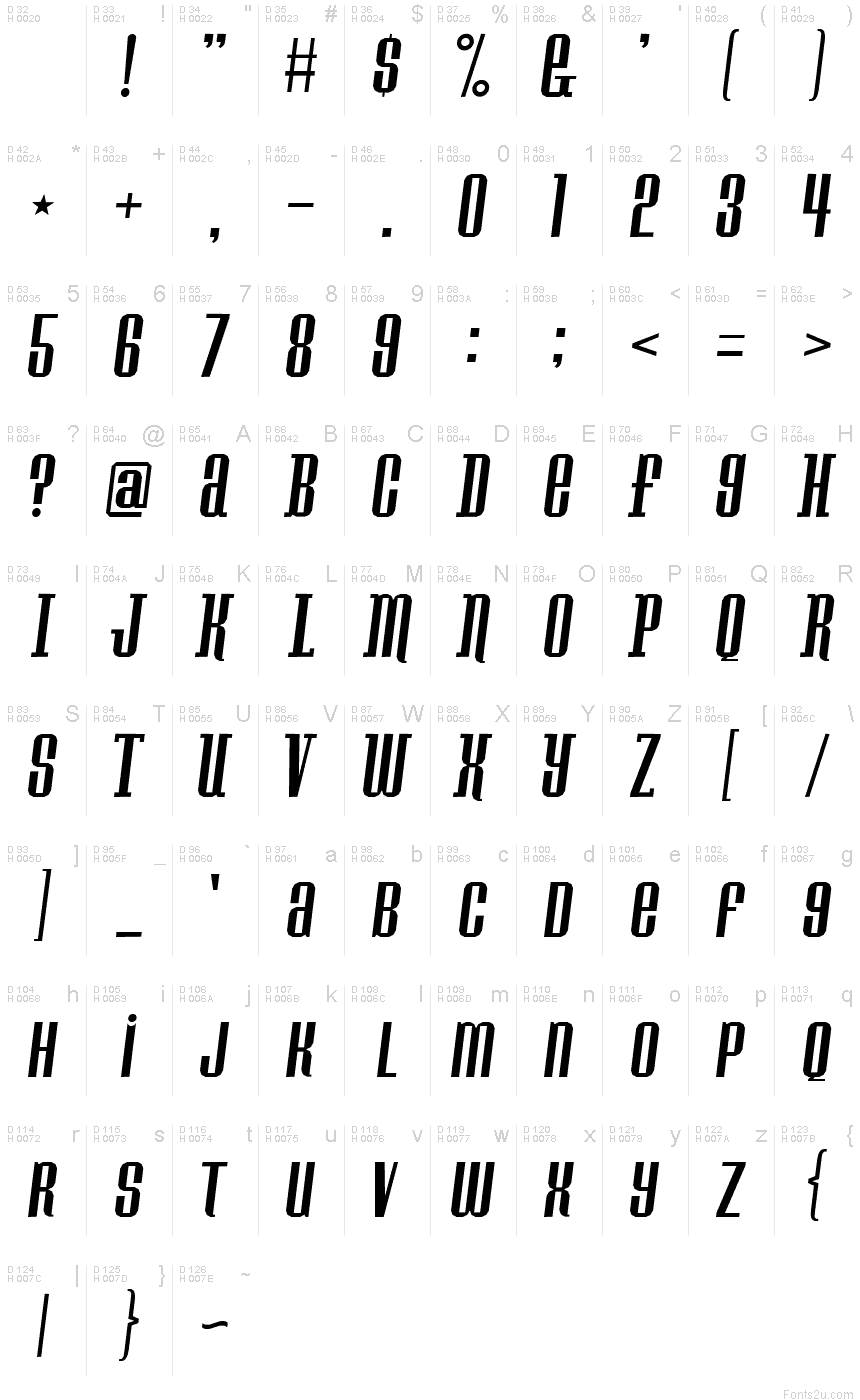
Konspiracy Theory slant
Konspiracy Theory slant autorstwa Jakoba Fischera to nowoczesny, darmowy krój typu display o ostrym, pochylonym charakterze. Wysokie, wąskie litery dynamicznie przecinają linię pisma, nadając każdemu słowu poczucie ruchu i pilności – niczym nagłówki w samym środku akcji. Ciężkie kreski sprawiają wrażenie gęstych i solidnych, a ciasny rytm form sprawia, że tekst wygląda na zwarty i wyrazisty, nawet przy bardzo dużych rozmiarach.
Wykorzystaj Konspiracy Theory slant, aby dodać energii logotypom gier, tytułom filmów science-fiction, brandingowi e-sportowemu, plakatom wydarzeń technologicznych, okładkom albumów czy przyciągającym wzrok miniaturkom na YouTube. Ten darmowy font najlepiej sprawdza się w przypadku krótkich słów pisanych wielkimi literami, którym warto dać odrobinę oddechu. Jako uzupełnienie wybierz prosty, geometryczny bezszeryfowy krój w mniejszym rozmiarze, aby nie odciągać uwagi od drapieżnego, konspiracyjnego klimatu tytułu głównego.